Tipografía Efectiva: Optimizando la Legibilidad
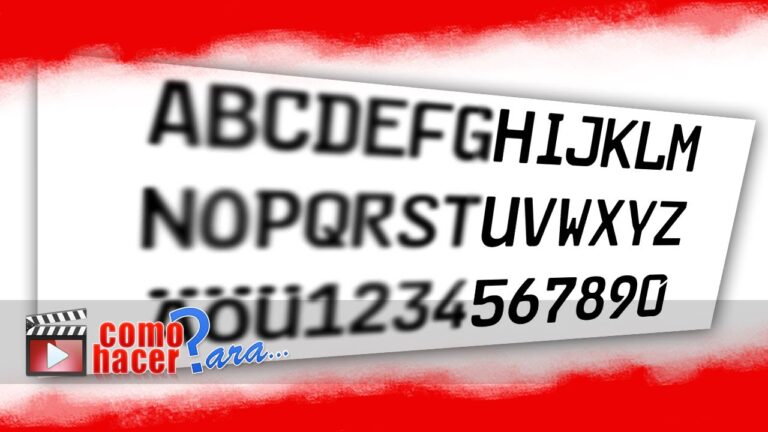
En un mundo donde la información fluye a gran velocidad, la legibilidad se convierte en un factor fundamental para captar y mantener la atención del lector. Optimizando la legibilidad con tipografía adecuada, no solo se mejora la experiencia de lectura, sino que también se potencia la efectividad del mensaje que se desea transmitir. Elegir fuentes que sean visualmente armoniosas y que se adapten al contenido puede marcar la diferencia entre un texto que se ignora y uno que se disfruta. En este artículo, inspeccionaremos cómo la tipografía puede transformar la comunicación escrita y elevar su impacto.
¿Cuál es el significado de la legibilidad en la tipografía?
La legibilidad en la tipografía se refiere a la facilidad con la que un texto puede ser leído y comprendido por el lector. Este concepto engloba diversos aspectos tipográficos, como el tamaño y el tipo de letra, así como el espaciado entre caracteres y líneas. La presentación visual de un texto juega un papel fundamental en su accesibilidad, ya que una disposición adecuada puede facilitar la lectura y mantener el interés del lector.
Además de los elementos tipográficos, la legibilidad también abarca el estilo y la claridad de la exposición. Un texto bien estructurado, con un lenguaje claro y conciso, permite que el lector comprenda el mensaje sin esfuerzo. La forma en que se organiza la información, incluyendo el uso de encabezados y párrafos, contribuye a que los lectores sigan el hilo argumentativo de manera rendidora.
Finalmente, la legibilidad no solo se trata de la tipografía y el estilo, sino también de la adecuación del contenido al público objetivo. Es esencial considerar el contexto y las expectativas del lector al seleccionar la tipografía y el estilo de redacción. Un enfoque cuidadoso en estos aspectos puede mejorar considerablemente la experiencia de lectura, haciendo que el mensaje sea más accesible y atractivo.
¿Qué se entiende por legibilidad en tipografía?
La legibilidad en tipografía es un aspecto fundamental que afecta la forma en que los lectores perciben y comprenden el texto. Una fuente bien diseñada presenta un espaciado adecuado que permite distinguir cada carácter de manera clara y sencilla. Esto facilita la lectura fluida y evita la fatiga visual, lo que resulta fundamental en entornos donde la información se consume rápidamente.
El ancho y el peso de los caracteres también juegan un papel decisivo en la legibilidad. Fuentes que son demasiado estrechas pueden dificultar la identificación de letras individuales, especialmente en letras minúsculas y en palabras poco familiares. Por otro lado, aquellas que tienen un mayor peso y un diseño más claro suelen ofrecer una mejor experiencia de lectura, ya que destacan los caracteres y mejoran el reconocimiento visual.
En resumen, la legibilidad tipográfica no solo depende del diseño de la fuente, sino también de su espaciado, ancho y peso. Para maximizar la comprensión del texto, es esencial elegir fuentes que equilibren estos elementos, consintiendo así que los usuarios disfruten de una lectura sin obstáculos. La atención a estos detalles puede marcar la diferencia en la efectividad de la comunicación escrita.
¿Cuál es la tipografía más adecuada para aumentar la legibilidad en un material educativo?
Para mejorar la legibilidad en materiales educativos, es fundamental elegir una tipografía adecuada que facilite la comprensión del contenido. Las fuentes sans-serif, como Arial y Helvetica, son perfectas para el cuerpo del texto, ya que ofrecen claridad y simplicidad. Por otro lado, las fuentes serif, como Times New Roman y Georgia, aportan un toque de elegancia y son ideales para títulos y subtítulos, creando un contraste visual que guía al lector. Al combinar estos estilos, se logra un diseño armonioso y efectivo que potencia la experiencia de aprendizaje.
Claves para Mejorar la Comprensión Visual
La comprensión visual es una habilidad esencial que nos permite interpretar y analizar información de manera rendidora. Para mejorarla, es fundamental desarrollar una observación activa, donde se preste atención a los detalles y se practique la identificación de patrones. Leer imágenes, gráficos y diagramas con un enfoque crítico facilita la conexión entre conceptos y mejora la retención de información. Además, la práctica permanente, como realizar ejercicios de análisis visual, puede ayudar a fortalecer esta habilidad.
Otra clave para mejorar la comprensión visual es la diversificación de las fuentes de información. Incorporar diferentes tipos de materiales, como videos, infografías y presentaciones interactivas, enriquece la experiencia de aprendizaje y permite abordar los contenidos desde múltiples perspectivas. Al combinar estos recursos, se fomenta una comprensión más profunda y se estimula el pensamiento crítico. Con dedicación y variedad en el enfoque, es posible potenciar considerablemente la capacidad de interpretar visualmente el mundo que nos rodea.
La elección de una tipografía adecuada es fundamental para optimizar la legibilidad de cualquier texto. Al priorizar un diseño tipográfico que combine claridad y estética, no solo se mejora la experiencia del lector, sino que también se potencia la efectividad del mensaje. Al final, una tipografía bien seleccionada puede ser el puente que conecta ideas y emociones, facilitando una comunicación más fluida y atractiva.